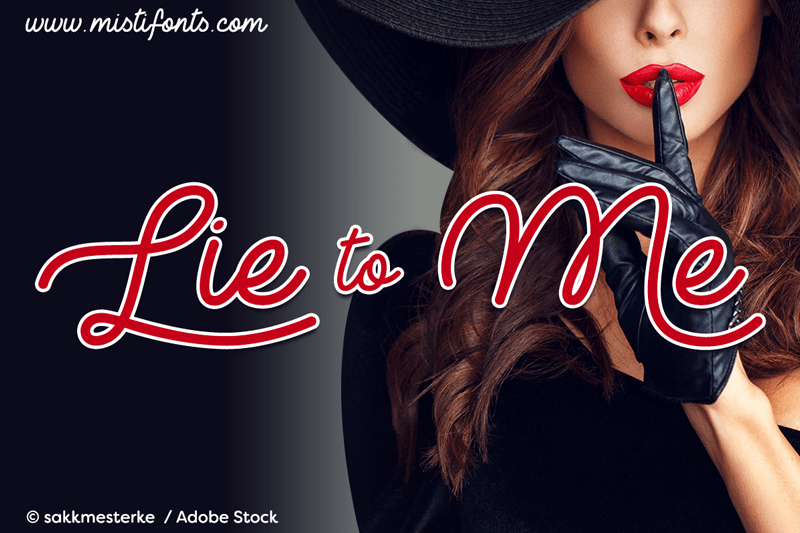
Lie to Me Script Font – Download Grátis
Introduzimos Lie to Me Script Font! Desenvolvida pelo designer Misti’s Fonts, esta font script foi projetada para dar beleza a qualquer texto que você use. Com seu estilo autêntico que faz com que se pareça mais natural, é perfeita para uso em sua marca, frases escritas à mão, logomarcas, cabeçalhos, outdoors, roupas, embalagens de produtos, cartões de visita e muito mais. Não importa o propósito, Lie to Me Script Font é a escolha ideal para você querer dar um toque autêntico e natural aos seus projetos gráficos.